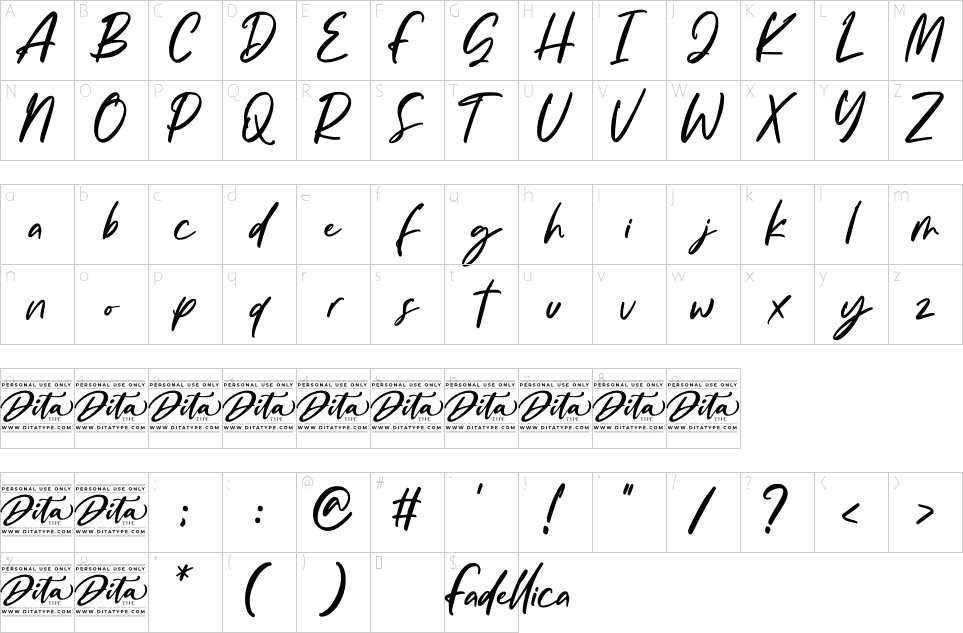
Fadellica Font – Download Grátis
Descubra a beleza da Fadellica, uma fonte grátis para Windows e Mac. Desenvolvida pela Dita Type, Fadellica é uma escolha perfeita para quem busca uma fonte com um estilo natural e envolvente. Com apenas 2,397 downloads, Fadellica se destaca como uma opção versátil e confiável para projetos de design gráfico. Seja para criar títulos impressionantes ou letras sutis, Fadellica traz uma sensação de tranquilidade e conforto, adaptável para diversos estilos de design. Aprecie a qualidade do seu projeto, sabendo que está usando uma fonte gratuita de alta qualidade. Fadellica é mais do que uma fonte: é uma paixão para os profissionais do design.